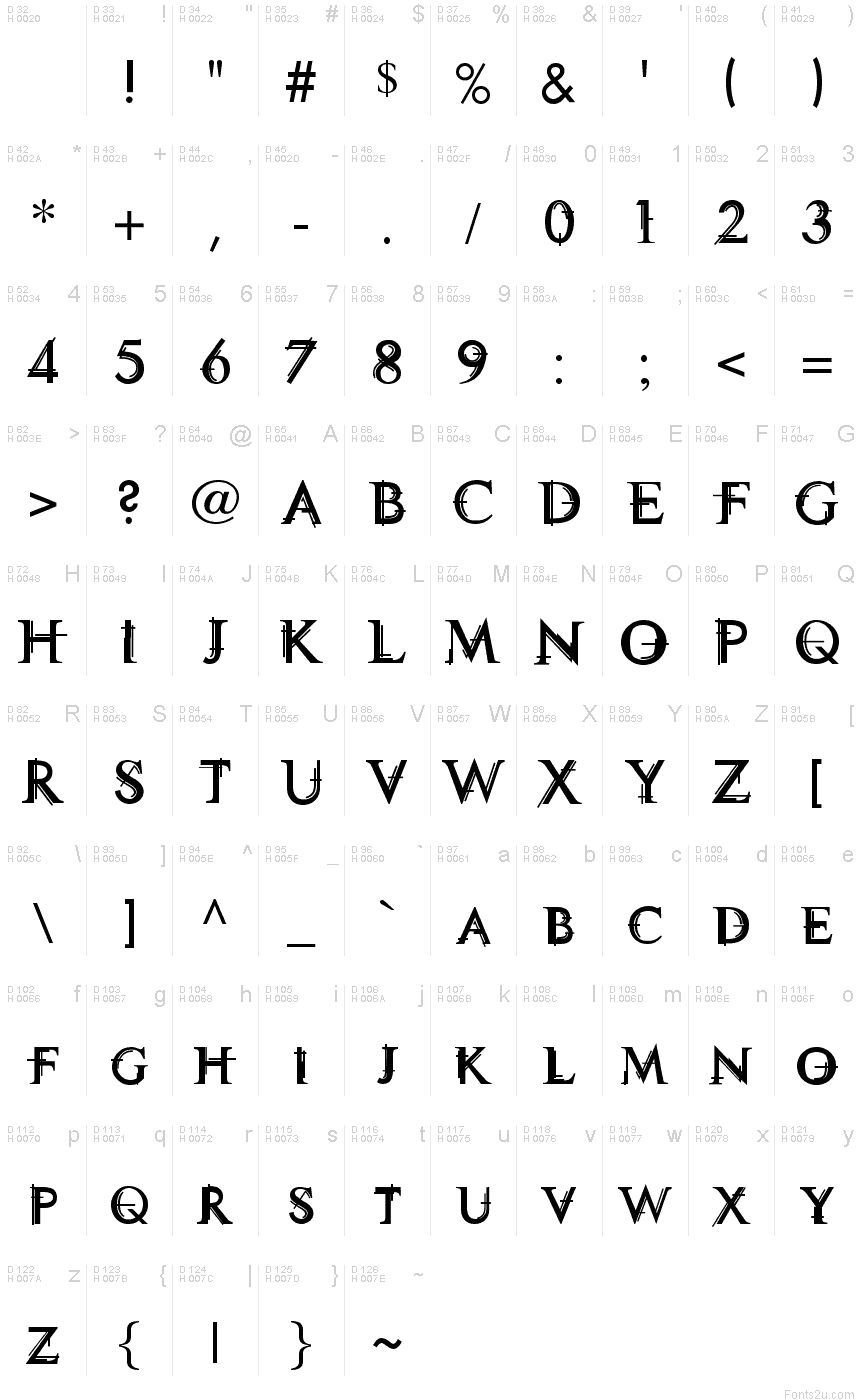
Technovia Caps od Zang-O-Fonts to darmowy, techniczny krój typu display o zniekształconej formie, z ostrymi, kontrastowymi literami przeciętymi cienkimi, poziomymi i pionowymi liniami. Wielkie litery przywodzą na myśl futurystyczne szyldy z późnych lat 90. – eleganckie w zarysie, a jednocześnie celowo zaburzone przez powtarzające się przerwy typu „scan-line” i przycięte łączenia.
Krój świetnie sprawdzi się na plakatach, okładkach albumów, ulotkach klubowych, w brandingu gier i opakowaniach w stylu sci-fi, gdzie liternictwo staje się częścią systemu graficznego. Jako darmowy font, doskonale nadaje się również do krótkich nagłówków, plansz tytułowych i monogramów, ponieważ wycięte detale nadają nawet pojedynczym literom tę futurystyczną, syntetyczną energię.